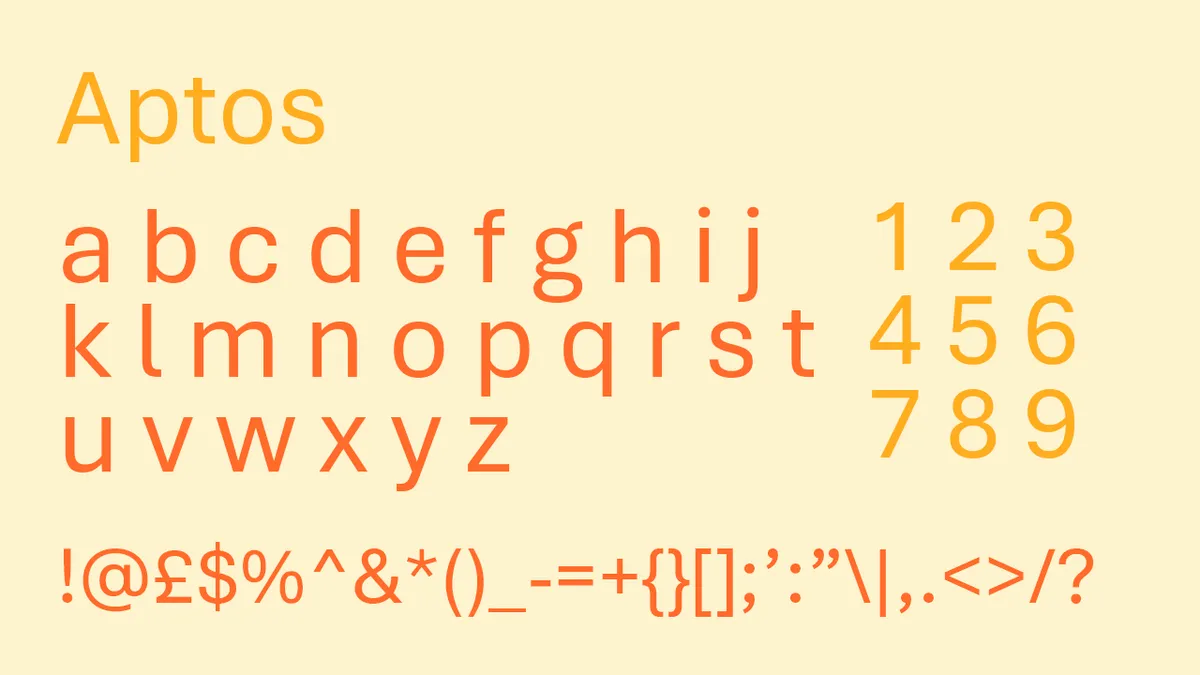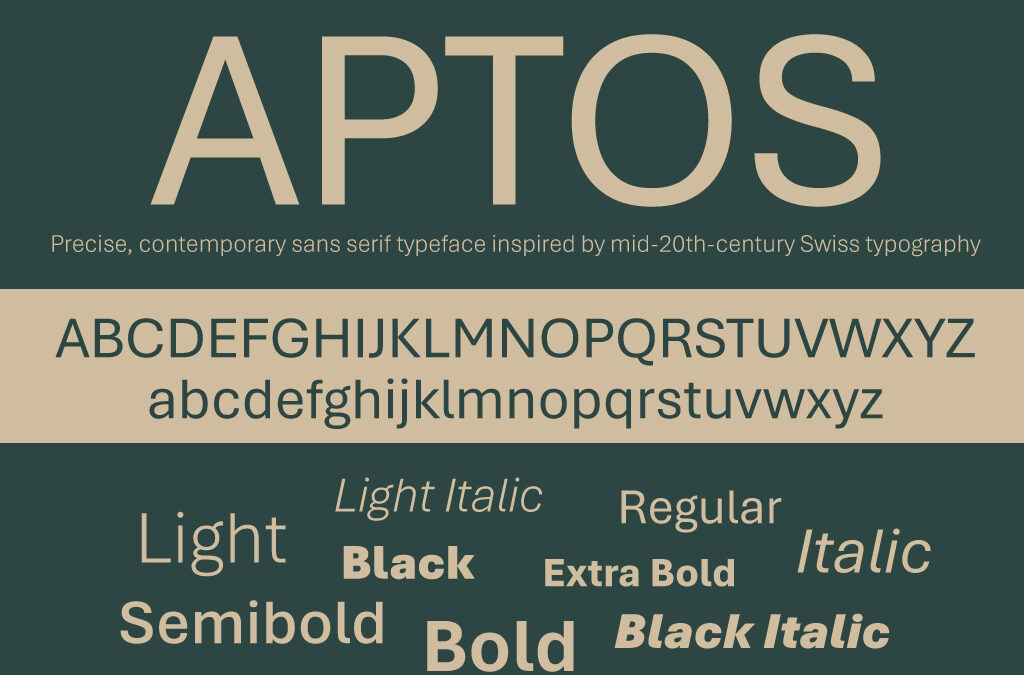
Download font Aptos được nhiều người tìm kiếm sau khi Microsoft giới thiệu Aptos là font mặc định mới trong Microsoft Office. Font này được thiết kế để thay thế Calibri, mang lại khả năng hiển thị rõ ràng và hiện đại hơn trong văn bản.
Tham khảo font Aptos – font mặc định mới của Microsoft Office
Font Aptos được Microsoft giới thiệu như một bước thay đổi lớn trong hệ thống font mặc định của bộ Office. Sau nhiều năm sử dụng Calibri, Microsoft đã phát triển Aptos để mang đến kiểu chữ hiện đại, dễ đọc và phù hợp với nhiều loại tài liệu khác nhau.
Khi download font aptos, bạn sẽ thấy font có thiết kế khá cân đối với nét chữ rõ ràng. Điều này giúp văn bản hiển thị tốt trên cả màn hình máy tính lẫn khi in ấn.
Một số đặc điểm nổi bật của font Aptos gồm:
- Thiết kế chữ hiện đại, dễ đọc.
- Khoảng cách ký tự cân đối.
- Hiển thị tốt trên màn hình và khi in.
- Phù hợp cho tài liệu văn phòng và thuyết trình.
Font Aptos thường được dùng trong trường hợp nào?
Font Aptos được thiết kế chủ yếu cho môi trường văn phòng, vì vậy thường xuất hiện trong nhiều loại tài liệu chuyên nghiệp.
- Tài liệu văn phòng (Microsoft Word): Được sử dụng làm phông chữ mặc định cho các loại văn bản như báo cáo, hợp đồng, công văn hoặc tài liệu nội bộ. Thiết kế Sans Serif hiện đại, rõ ràng giúp nội dung dễ đọc và tạo cảm giác chuyên nghiệp.
- Email công việc: Nhờ khả năng hiển thị tốt trên cả máy tính và điện thoại thông minh, font Aptos rất phù hợp để soạn thảo email. Kiểu chữ gọn gàng giúp người nhận dễ theo dõi nội dung và giảm cảm giác rối mắt khi đọc.
- Bài thuyết trình (Microsoft PowerPoint): Với cấu trúc chữ không chân và khoảng cách ký tự hợp lý, Aptos giúp nội dung trên slide dễ đọc từ xa, đặc biệt hiệu quả khi trình chiếu trên màn hình lớn hoặc thiết bị có độ phân giải cao.
- Sơ yếu lý lịch – CV/Resume: Aptos là lựa chọn hiện đại thay thế cho các font quen thuộc như Calibri, Arial hoặc Times New Roman. Kiểu chữ rõ ràng giúp CV trông chuyên nghiệp hơn và dễ đọc với hệ thống ATS (Applicant Tracking System).